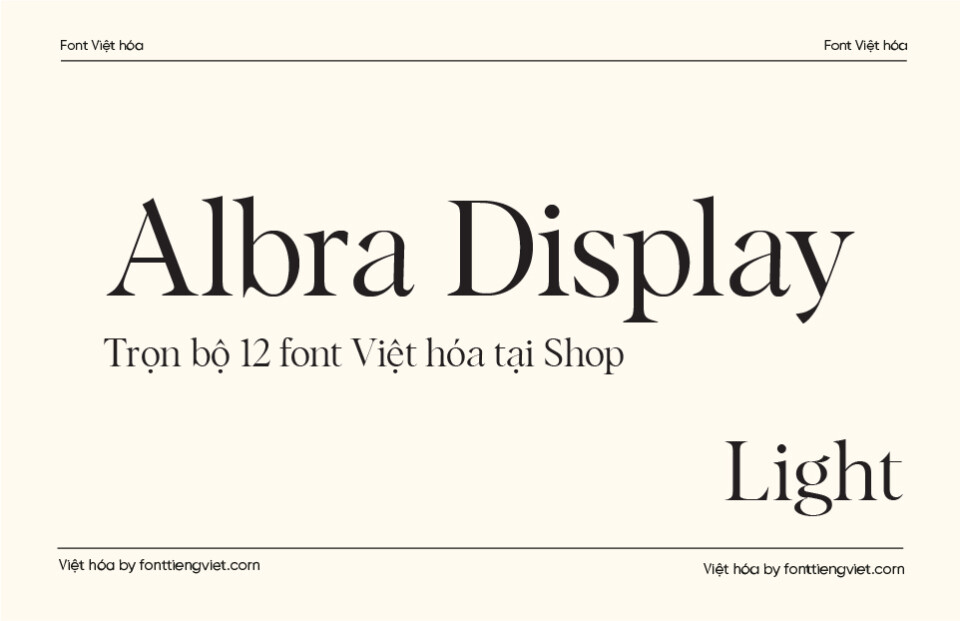
Font Việt hóa 1FTV VIP Albra Display Light – Đẳng cấp thiết kế hiện đại và tinh tếGiới thiệu về Font Việt hóa 1FTV VIP Albra Display LightTrong thế giới thiết kế đồ họa ngày nay, việc lựa chọn một bộ Font Miễn Phí chất lượng đóng vai trò sống còn trong việc tạo nên linh hồn cho sản phẩm. Font Việt hóa 1FTV VIP Albra Display Light nổi lên như một sự lựa chọn hàng đầu cho những ai yêu thích phong cách thanh lịch, tối giản nhưng vẫn đầy quyền lực. Đây là phiên bản đặc biệt được tinh chỉnh kỹ lưỡng về dấu tiếng Việt, giúp các nhà thiết kế tại Việt Nam dễ dàng ứng dụng vào các dự án từ in ấn đến truyền thông kỹ thuật số. Với độ mảnh mai đặc trưng của dòng Light, bộ chữ này mang lại cảm giác thoáng đãng, dễ chịu cho người xem ngay từ cái nhìn đầu tiên.Đặc điểm nổi bật của Font Việt hóa 1FTV VIP Albra Display LightThiết kế thanh mảnh và sang trọngĐặc trưng lớn nhất của Font Việt hóa 1FTV VIP Albra Display Light chính là các đường nét thanh mảnh, sắc sảo. Các nét chữ được gọt giũa tỉ mỉ, tạo nên một cấu trúc hình học cân đối nhưng không kém phần mềm mại. Kiểu dáng này cực kỳ phù hợp cho các tiêu đề lớn, bìa tạp chí thời trang hoặc các ấn phẩm cao cấp cần sự tinh tế tuyệt đối. Khi sử dụng bộ font này, trang thiết kế của bạn sẽ toát lên vẻ chuyên nghiệp và hiện đại, giúp thông điệp truyền tải trở nên nhẹ nhàng nhưng vẫn có sức nặng đáng kể.Khả năng hiển thị tối ưu trên nhiều nền tảngDù sở hữu nét chữ mỏng, nhưng Font Việt hóa 1FTV VIP Albra Display Light vẫn đảm bảo được độ hiển thị rõ nét trên cả màn hình máy tính lẫn bản in vật lý. Điều này có được nhờ vào sự tối ưu hóa khoảng cách giữa các chữ cái (kerning) và tỷ lệ khung hình chuẩn mực. Đối với các bạn học sinh và sinh viên, việc sử dụng bộ font này trong các bài thuyết trình hay thiết kế báo tường sẽ giúp nội dung trở nên bắt mắt và dễ tiếp cận hơn, tạo ra sự khác biệt so với các font chữ hệ thống thông thường.Ứng dụng thực tế của bộ font trong đời sống và giáo dụcSáng tạo trong học đường và thiết kế cá nhânKhông chỉ giới hạn trong giới chuyên nghiệp, Font Việt hóa 1FTV VIP Albra Display Light còn là công cụ tuyệt vời cho môi trường học đường. Các thầy cô giáo có thể dùng font này để làm tiêu đề bài giảng sinh động, trong khi học sinh có thể áp dụng vào việc làm Portfolio cá nhân hoặc trang trí các dự án ngoại khóa. Sự đơn giản của font chữ giúp người xem không bị phân tâm, tập trung hoàn toàn vào nội dung cốt lõi mà người sáng tạo muốn gửi gắm.Xu hướng sử dụng font việt hóa hiện nayViệc sử dụng các font chữ đã được việt hóa chuẩn giúp tiết kiệm thời gian và tránh các lỗi hiển thị ký tự không mong muốn. Font Việt hóa 1FTV VIP Albra Display Light đáp ứng đầy đủ các tiêu chuẩn về bảng mã Unicode, tương thích tốt với các phần mềm đồ họa phổ biến như Adobe Photoshop, Illustrator hay Canva. Đây chính là bước đệm hoàn hảo để các bạn trẻ bắt đầu hành trình khám phá thế giới thiết kế đầy màu sắc của mình.Kết luận về giá trị của Font Việt hóa 1FTV VIP Albra Display LightCó thể khẳng định rằng, Font Việt hóa 1FTV VIP Albra Display Light là một mảnh ghép không thể thiếu trong bộ sưu tập của bất kỳ nhà sáng tạo nội dung nào. Với sự kết hợp hoàn hảo giữa nét thẩm mỹ phương Tây và sự tinh chỉnh phù hợp với ngôn ngữ Việt, bộ font này hứa hẹn sẽ nâng tầm mọi sản phẩm thiết kế. Hãy trải nghiệm ngay sự khác biệt mà nó mang lại để thấy rằng cái đẹp đôi khi đến từ những điều giản đơn nhất. Để sở hữu bộ chữ tuyệt đẹp này, bạn có thể tìm kiếm thông tin tại Font Miễn Phí, Font Việt Hóa, Font Việt hóa 1FTV VIP Albra Display Light và bắt đầu hành trình sáng tạo không giới hạn của mình ngay hôm nay.
Font Việt hóa 1FTV VIP Albra Display Light